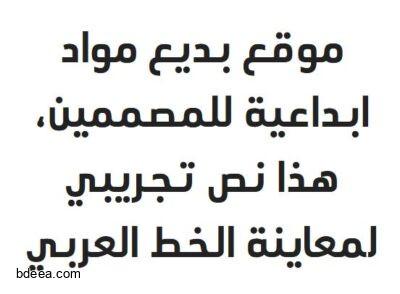
حمّل خط مودرن عربي Arabic Modern font ttf واستمتع بمظهر أنيق وواضح للنصوص العربية في التصاميم والمستندات والمواقع. يتميز الخط بتناسق الحروف وسهولة القراءة، مما يجعله مناسبًا للعناوين والنصوص والتقارير والفواتير ومختلف الاستخدامات المكتبية والتصميمية.